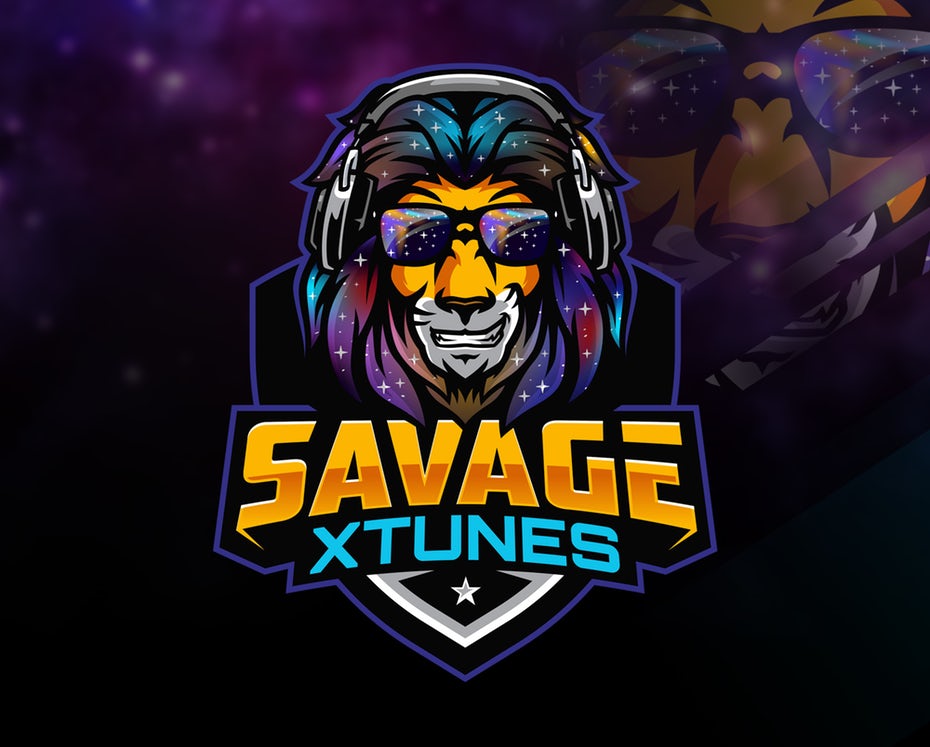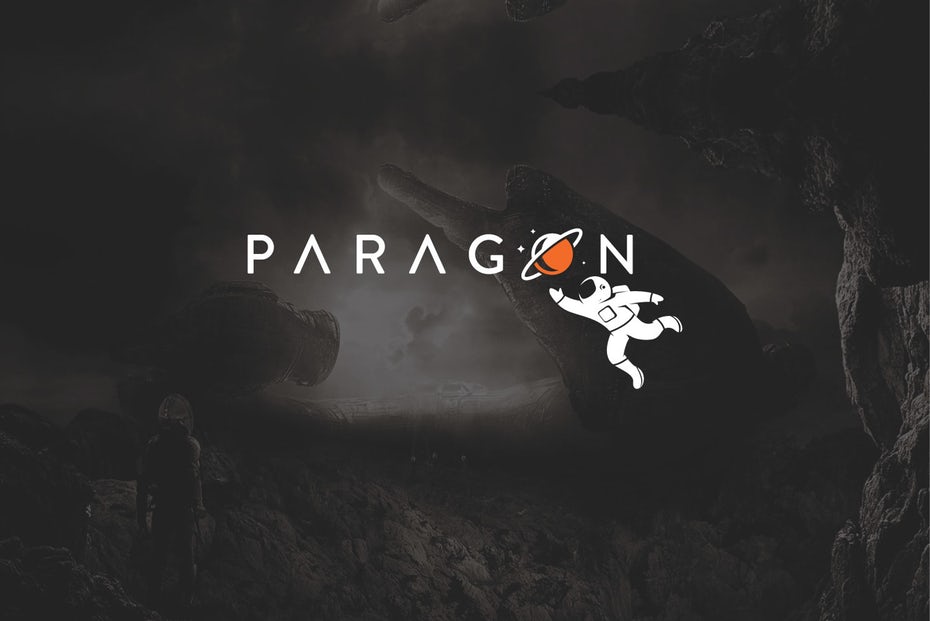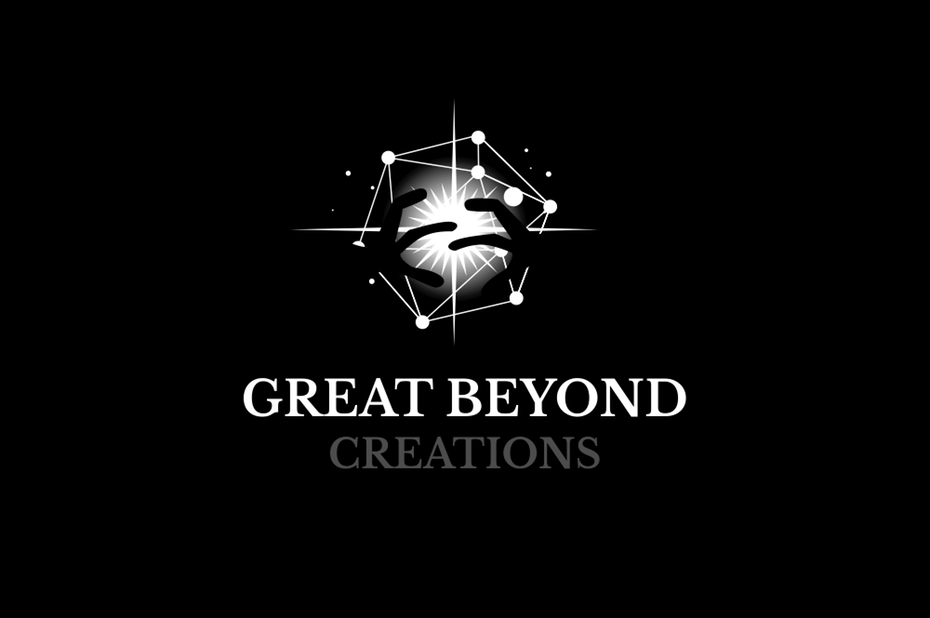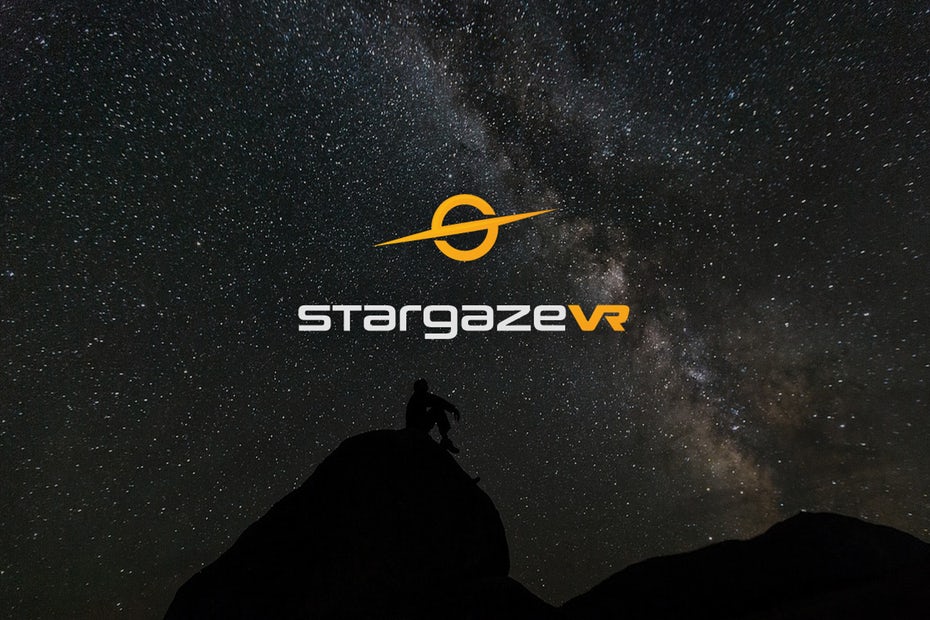
让未来主义改变你的设计!
为什么生活在现在,而你可以生活在未来?时间机器可能还不存在,但在它们出现之前,你可以用一个未来派的标志把你的品牌放在时代的最前沿。
任何行业的任何一家公司都可以使用未来派的标志来传达这样一种信息:它领先于潮流。在一些行业,如科技和制药行业,这样做是意料之中的。在其他方面,比如景观美化,未来派的标志并不是明显的选择,这正是为什么它能让你的品牌脱颖而出的原因。
未来主义的标志有很多种形式,这就是为什么我们把这些技巧结合在一起,引导你进入未知的旅程。如果运气好的话,你最终会把自己的品牌写进设计的未来。
未来派标志的特点是什么?
那么,你如何使你的标志看起来未来派?这是一个棘手的问题,因为没有客观的方法来衡量什么是未来主义的,什么是非未来主义的。而现在感觉到未来主义的东西不会永远有这种感觉,因为随着时间的推移,我们对什么是新的,什么是现代的,什么是复古的想法也会有这种感觉。有些品牌有意通过复古未来主义来追求过时的未来主义,比如:
但像这些标志更倾向于“复古”,而不是“未来”。创建一个让人感觉未来的标志,意味着要深入观察你的黑色镜子,挖掘出我们目前对“未来”的所有不同看法。现在,这是一个气候发生了重大变化(或没有变化)的世界,在这里宇宙的奥秘就不那么神秘了,所有的事物都通过数字景观连接在一起,计算机也接管了一切(希望不是字面意义上的)。
下一步是用视觉传达这些概念,我们收集了一些优秀的未来主义标志设计和提示来向您展示。
太空时代元素
这就是为什么未来会有如此多的故事涉及太空旅行的原因,这是人类合乎逻辑的下一步。因此,将太空时代的元素融入到你的标志设计中,无疑会给你一种未来感。
有几种不同的方法可以做到这一点:你可以使用航天飞机、宇航员、恒星和行星的文字图像,或者你可以用几何图形以更抽象的方向来让人们想起像星云的星座或梯度。最重要的是要创造一个让人感觉不到这个世界的标志。
未来科技的一瞥
未来主义标志不可避免地受到科技启发,无论它们是属于科技公司还是仅仅是暗示我们以科技为中心的生活方式。如果不承认技术在推动我们的社会发展中所起的作用,就不可能有未来主义。
在你的标志中,用让人联想到节点、网络和替代能源的图像来证明这一点。这可能意味着一个紧密缠绕电路的背景,或者是一些不太明显的技术,比如使用绿色或金色的电路板。使用高光泽金属来提高你的标志的未来感,因为在未来,一切都是闪亮和新的。
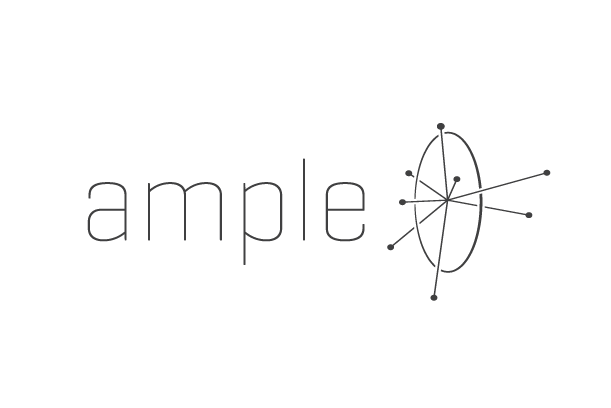
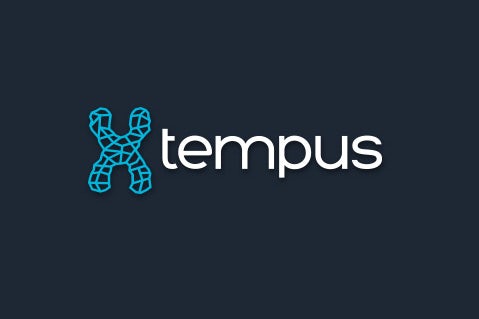
科学典故
包含生命微观结构块(如DNA螺旋体和原子)的标识让人觉得是未来派的,因为尽管它们自大爆炸以来就存在,但人类最近才开始研究和理解它们。
理解生命的微观组成部分,推动着我们理解世界。
用以下元素创建一个受科学启发的徽标:
1.文字元素,直接从周期表
2.DNA螺旋
3.原子及其组分
4.细胞
5.微生物
6.实验室工具
即使你的作品不在科学领域,一个螺旋线的描绘可以代表一个通往进步和创新的阶梯,而一些细胞节点可以给你的标志未来的外观,同时保持一切抽象。
未来的字体
你的未来主义标志需要一个未来主义的字体。
一个流行的风格是虫状曲线和极简主义,灵感来自美国宇航局标志。这个单词标记其实很古老并不重要,因为它已经与太空探索联系了几十年。
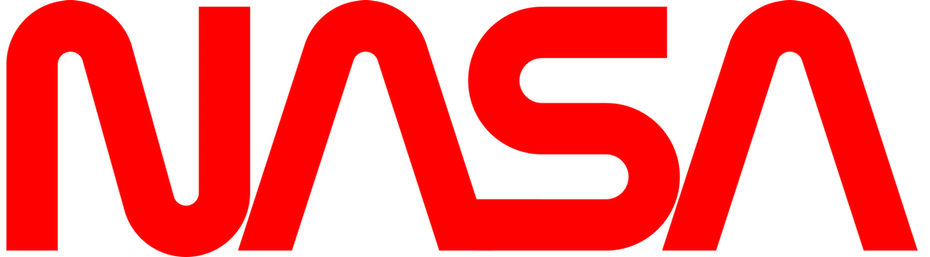
其他未来感的字体具有硬角度,几何图形,全部大写和对称字体。通常,它们是大胆的,带有压花和镀铬,反映了机器的外观。当他们不大胆的时候,他们就像代码一样薄而实用。
动力标志
今天,一切都在联系。门铃已经连接到智能手机,智能手机已连接至银行帐户。如果你记得给电池充电的话,你的指尖就有很大的能量。
当你想到这一点时,未来会越来越关注能源,这就是为什么在你的标志上发光可以让它感觉它已经转向这种生动的趋势。你可以用你的标志上的一个亮点来完成,模仿电子产品的开关灯。或者使用扩散霓虹灯创造一个具有网络朋克氛围的未来主义标志。如果做对了,你的标志将像明日世界的灯塔一样闪耀。
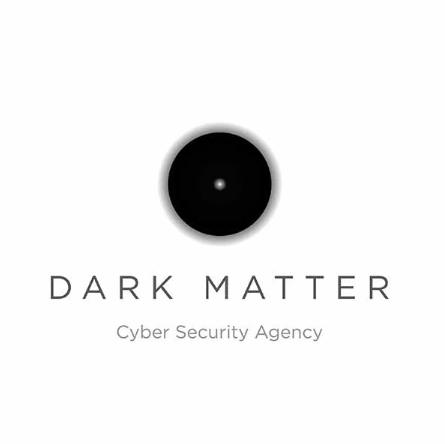
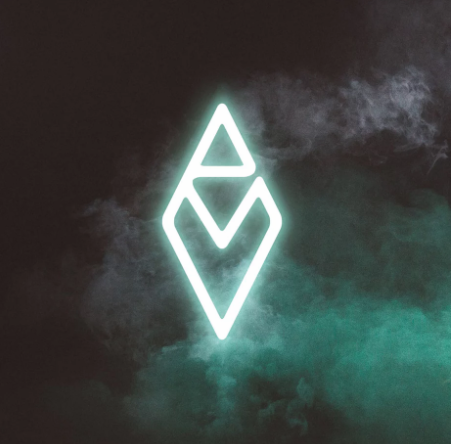
用未来风格的标志来发展你的品牌
无论你的行业是否与未来科技有关,你都可以让你的品牌看起来和感觉像是一个具有未来标志的尖端产品。
通过选择一种超前的外观,你可以为你的竞争对手设定步伐。